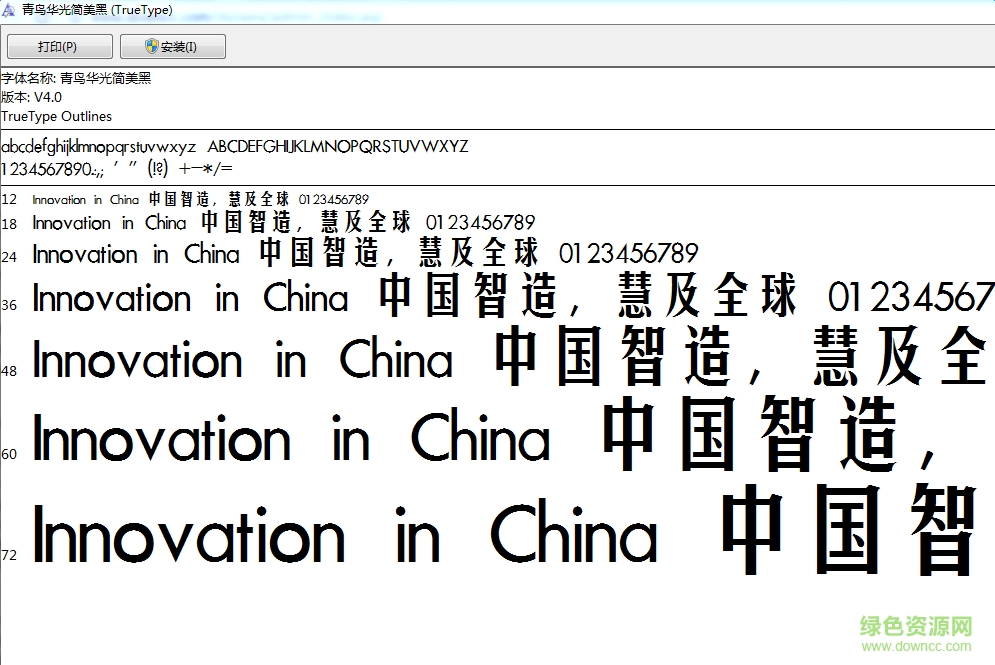
青鳥(niǎo)華光簡(jiǎn)美黑字體是一款清新簡(jiǎn)約風(fēng)格字體軟件,青鳥(niǎo)華光簡(jiǎn)美黑體以工整粗黑的筆畫(huà)給人非常簡(jiǎn)單明了的感覺(jué),非常的醒目,適用于各大海報(bào)廣告標(biāo)題的書(shū)寫(xiě),還有更多好看字體歡迎到綠色資源網(wǎng)下載使用!